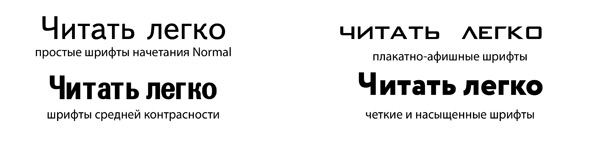
Лучшие шрифты для рекламных материалов: советы по выбору и использованию
Выбор шрифта играет ключевую роль в восприятии рекламы. Хорошо подобранный шрифт помогает выделить важную информацию и делает рекламный материал более привлекательным для целевой аудитории. В этой статье вы найдете советы, как выбрать шрифты, которые эффективно передают ваш посыл и усиливают визуальное воздействие рекламы.
При выборе шрифта для рекламы важно учитывать аудиторию: шрифт должен быть легким для восприятия и соответствовать стилю бренда.
Не стоит использовать слишком много разных шрифтов в одном рекламном материале — это может сделать его перегруженным и трудным для восприятия.
Для заголовков лучше выбирать жирные и выразительные шрифты, которые привлекут внимание с первого взгляда.
Используйте контрастные шрифты для выделения ключевых элементов, например, акций или специальных предложений.
Не забывайте об удобочитаемости шрифта — слишком тонкие или декоративные шрифты могут затруднить восприятие текста.
Для текстов с длинными описаниями лучше выбирать простые, без засечек шрифты, которые легко читаются на экранах разных устройств.
Следите за правильным сочетанием шрифта с цветом фона, чтобы текст оставался читаемым в любых условиях.
Используйте шрифты, которые соответствуют общему стилю вашего бренда или продукта, чтобы создать целостное и узнаваемое визуальное оформление.
Не бойтесь экспериментировать с нестандартными шрифтами, но помните, что они должны не только выделяться, но и быть понятными.
При работе с текстами на нескольких языках учитывайте локальные особенности восприятия шрифтов, чтобы избежать недоразумений.